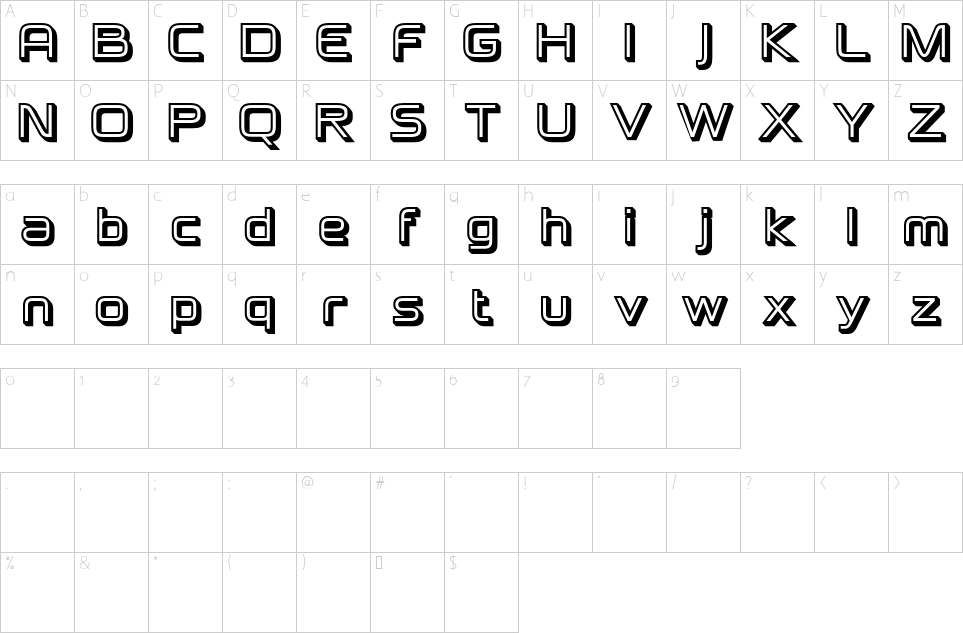
Descubra a beleza e a elegância da Megatrans font, uma proposta de fonte gratuita para Windows e Mac. Desenvolvida pela Craft Supply Co, esta fonte é uma escolha incrível para designers e aficionados do design que buscam uma opção moderna e versátil. Com seu design cuidadosamente pensado e detalhado, a Megatrans promete uma experiência de escrita agradável e uma aparência esteticamente atraente em seus projetos. Com sua disponibilidade gratuita e fácil download, a Megatrans é uma ótima escolha para aqueles procurando por uma fonte de qualidade sem precisar gastar muito. E se você é um entusiasta da arte digital e gosta de experimentar novas fontes, a Megatrans pode ser um excelente ponto de partida para explorar e experimentar uma grande variedade de opções de design.